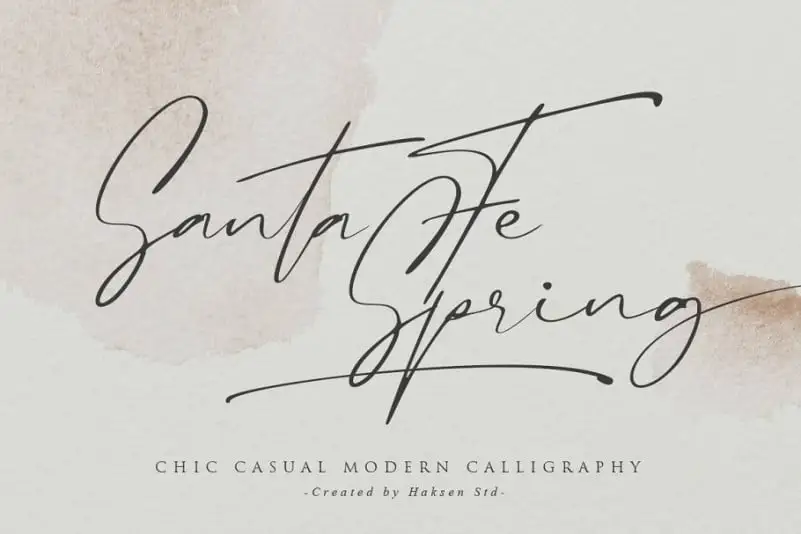
Santa Fe Spring Handwritten Font – Download Grátis
A Santa Fe Spring Handwritten Font é uma maravilhosa escolha para quem busca personalidade em seus materiais digitais. Esse script feito à mão possui um tom natural e suave, criado por Haksen. Perfeito tanto para assinaturas exclusivas quanto para embalagens de produtos, convites de casamento e promoções inovadoras, a fonte oferece uma variedade completa de letras maiúsculas e minúsculas, números e pontuação, além de símbolos multilíngues. O conjunto inclui também swashes para começos e encerramentos de linhas, ligaduras personalizadas que adicionam um toque autêntico à sua escrita, criando uma aparência extremamente realista. Seja você designer gráfico, editor de conteúdo ou profissional de marketing, a Santa Fe Spring Handwritten Font é uma escolha ideal para transformar seu trabalho em algo único e imprimivelmente elegante.